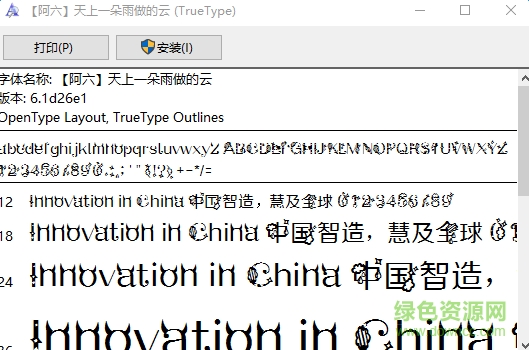
天上一朵雨做的云
天上一朵雨做的云字體是一款很特殊的電腦字體,這款字體就像它的名字所說那樣有雨有云,所以在寫出來的字上面也是有雨有云這些裝飾物的,是不是很神奇呢,喜歡的朋友就快來綠色資源網(wǎng)下載吧。
天上一朵雨做的云字體是真的好特別,字體上面有裝飾物相信這是不常見的吧,也正是因為這樣這款字體才會顯得更特殊更有個性,歡迎大家來綠色資源網(wǎng)下載。